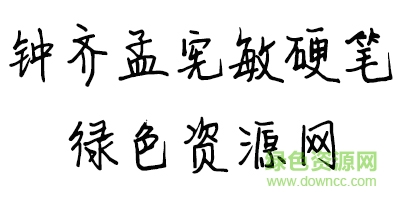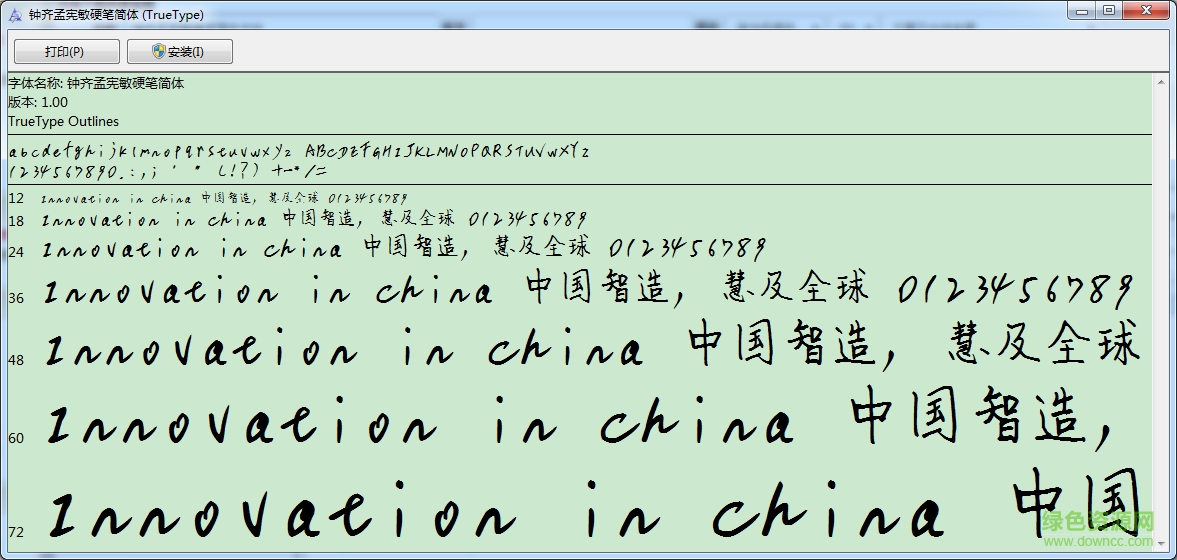
鐘齊孟憲敏硬筆簡(jiǎn)體是一款鋼筆硬筆簡(jiǎn)體字體,這款字體構(gòu)造端正,字跡清晰,展現(xiàn)出一種清新秀逸之感,喜歡這款字體的朋友可以來(lái)綠色資源網(wǎng)下載體驗(yàn)喲!
鐘齊孟憲敏硬筆簡(jiǎn)體是一款應(yīng)用于設(shè)計(jì)方面的簡(jiǎn)體中文字體,該字體純屬手工輸入,字形瀟灑大方,效果非常不錯(cuò),能夠應(yīng)用于簽名設(shè)計(jì)、平面設(shè)計(jì)、名片設(shè)計(jì)、廣告創(chuàng)意、印刷包裝等領(lǐng)域,有喜歡的朋友快下載收藏吧。